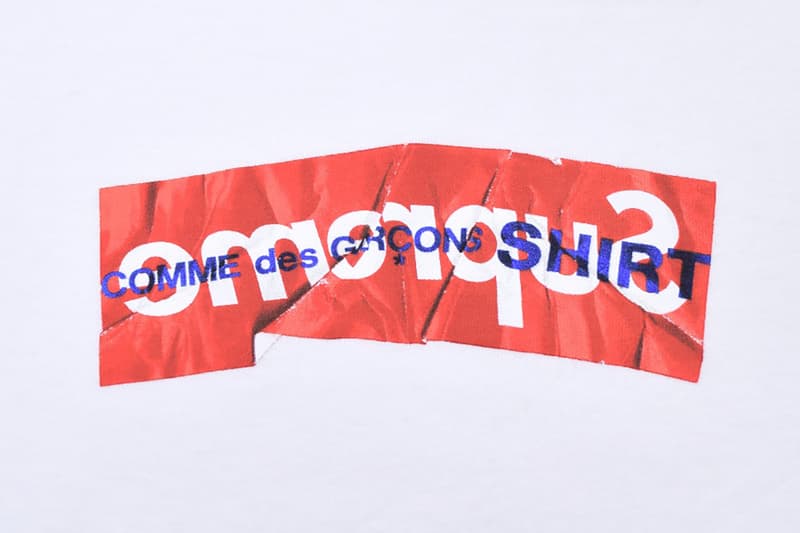
解析街头时尚品牌最爱用的 5 种字体
Supreme 与 COMME des GARÇONS 的 logo 能否诠释品牌风格?
字体,可视为时尚品牌的门面,是品牌与消费者沟通的桥梁。创意总监的更叠交替往往会带来字体重塑,旨在传达特定的情绪、力量、氛围,这意味著字体作为一种充满著复杂性的视觉语言,已成为时装、艺术、设计表达自我的重要工具。到底我们身边的街头、时装品牌或歌手、艺术家都青睐哪些字体,而这些字体,又是怎样反哺使用者,成为塑造品牌形象的重要一环。
Planet Cosmos
Raf Simons, Adidas
早前上映的《Ready Player One》成功打进 80、90 后观众市场,似乎再次强调源自上世纪 80 年代的游戏、科幻以及夜店文化正式回潮。Planet Kosmos 诞生于1996 年,丹麦图象设计师 Mads Rydahl 在日本漫画风格的基础上,创造出这款有著超高速摩托风驰电掣般神韵的字体,不但拥有日本漫画的风格,线条也颇具流畅性与未来感。虽然最初只是为某夜店创作,在互联网上免费开放下载多年,却在前年因被 Calvin Klein 创意总监 Raf Simons 和 Kanye West 同时买下字体的商用版权而进入大众视野。
而 Kanye West 早在 2016 年底就开始实际应用这款字体了,那段时间,他频繁在社交网络上分享自己穿著一条印有 Calabasas 字样的 adidas 运动裤。Calabasas 是他与 adidas 的首个合作企划,用的就是 Planet Kosmos,充满速度与未来感的科幻风格,不但完全击中了 Kanye 的内心(他是日本经典动画片《阿基拉》的忠实粉丝),也表现出与 adidas 三线 logo 近乎完美的契合度。无独有偶,在前年底买下 Planet Kosmos 的商用版权后,Raf Simons 就在同名品牌中小试牛刀,推出以「Venomous Friday」为主题的黑色卫衣与 Tote Bag,上面印有科幻感十足的 Planet Kosmos 字体。
有趣的是,字体设计者 Mads Rydahl 在接受《Racked》 的采访时表示,他并不想研究时装设计师们为何钟情于他的字体,也没有收取现金作为报酬,但他倒是向两位设计师要了一些个人私藏,包括新设计的衬衫、雷鬼音乐专辑等等。
SEGA
Sega
游戏株式会社是诞生于 1950 年代的一家日本电子游戏公司,生产家用游戏机及游戏软件,曾与任天堂、索尼电脑娱乐及微软并称「四大家用游戏机」制造商。今年年初以手术室主题成社交平台热门话题的 Gucci 2018 秋冬时装秀,除了以手持人头、《Game of Thrones》里的小恐龍等元素玩尽怪异时尚以外,一款全新的字体 Sega 也吸引了无数时装爱好者的注意。
SEGA 字体常见于 1980 年代充满迷幻色彩的街机游戏厅。创意总监 Alessandro Michele 在 Dad Shoes 鞋舌的 Logo、包包上以趣讽手法创造的「GUCCY」 字样上采用 SEGA,致敬 80 年代电子游戏文化。
Gothic Script
Yeezy
在尚未发明活版印刷之前,每本书都需要经过抄写员历时数月抄写,德国古腾堡为了模仿这些手写体,发明了这种艺术性还是远远大于实用阅读性的衬线体。是至今日,源于 12 世纪的 Gothic Script 已通过街头品牌、时装的运用、流行音乐的推广,掀起了一波「字体狂潮」。从 A$AP Mob 专辑,纽约品牌 SSUR、Matthew Williams 主导的创意单位 BEENTRILL,银饰品牌 Chrome Hearts,到 MISBHV、424、Born x Raised 等独立设计品牌…… 街头潮牌确实将中世纪的古老文字带回了现代。
2016 年 2 月,Kanye West 携手洛杉矶艺术家 Cali Thornhill Dewitt 共同打造演唱会「The Life Of Pablo」的周边商品 — The Life of Pablo 同名服装系列,包括 T 恤、卫衣以及牛仔外套,设计以清一色罗马字体歌词印刷为主。Cali 曾在接受独立杂志《032c》采访中提到这种字体的复兴:
「这个设计基于 80、90 年代的帮派文化,帮派成员死后人们会为他做一件这样的纪念 T 恤。」— Cali Thornhill Dewitt
Gothic Script 经常出现在上世纪 80 年代帮派成员的刺青及衣物上,也会用于印刷圣经,因此被西方人认为拥有保卫家园的宗教力量,更有一丝自我保护的意味。随后,Kanye 趁热打铁,借助 Yeezy Season 3 的发布,成功将此字体打造成全球范围现象级的流行。不过,也有设计师对品牌过量使用这种字体表示出担忧,试问那些脚踩 Yeezy 身著 Pablo 的年轻人,有谁真的了解 Season 3 背后卢旺达大屠杀的故事?或是 Gothic Script 背后的宗教意义及帮派关联呢?
Gothic Script 特殊的笔触与涂鸦艺术家的涂写工具相当相似,不出意料地也能与街头文化碰撞出火花。除了服饰之外,Gothic Script 元素不断地出现在音乐人的专辑封面和海报上,比如说唱团体 A$AP Mob 早在 Kanye West 之前就将该字体印在专辑和周边商品上。Vetements 2016 SS/FW 则以 Gothic Script 字体呈现如「Drink from me and live forever」等标语,并将其运用在夹克、卫衣和裤装上,带有几分暗黑浪漫的色彩。纽约时报曾指出:「Gothic Script 字体包含了十分多元的文化,并且折射出一种信仰与反叛。」
曾作为推动朋克运动主力军的朋克教母 Vivienne Westwood,恰恰选择了名为「Starnberg」的 Gothic Script 样式字体作为个人品牌的 Logo,打破时装品牌总是留给人中规中矩的视觉形象。英国设计师 John Galliano 在 2000 年 秋冬系列上亦选择大规模启用该字体。他将自己的照片、作品和新闻以报纸形式印在成衣上,版头就是以醒目的 Gothic Script 写著「Christian Dior Daily」字样。
Vivienne Westwood
Helvetica
论历史,它比不上 Bodoni(Vogue 杂志封面字体);论优雅,它亦比不上拥有法国血统的 Didot,论实用,它比不上 Times New Roman (论文专用字体),但它对现代主义的影响力无疑是划时代的,也是首款被纽约 MoMA 首次列为馆藏的字体;COMME des GARÇONS、RAF BY RAF SIMONS、American Apparel、苹果 iOS 7 系统、松下电器、纽约地铁站都用它,B Magazine 有一期还专门介绍了这款字体。
「Helvetica is everywhere. It’s like air. You can’t help breathing it in.」— 平面设计师,Michael Beirut
20 世纪上半叶,包豪斯运动席卷了整个欧洲,实用主义影响了建筑、绘画、工业及字体设计,无衬线字体凭藉容易辨识和阅读的字形,进入了设计界的主流。被誉为「无衬线字体的终极形态」的 Helvetica,以「刚正不阿」的形象、柔和中性的气质以及现代主义气息,受到了无数设计师、企业品牌的青睐。
Comme Des GarÇons
不按常理出牌的川久保玲为什么会使用看起来柔和中性的 Helvetica 作为 Logo 字体,很多人或许会认为这是一件有点反差萌、有点讽刺的事情。实际上,干净简洁的 Helvetica 与川久保玲有著不可言喻的默契:柔和中性支持开放性释读,同时又能展现丰富的个性和不言于表的自信。作家 Judith Thurman 曾在《纽约客》的一篇文章中提到:「川久保玲和 Coco Chanel 都是以平等为前提,认为每个女人都应该从自己的衣著上得到舒适与自信。」
在奉行 Logo 主义的今天,斜纹代表 Off-White™,而红底白字即象征著 Supreme;其极具辨识度的标识,一看就能看出是什么的品牌认同感。HBA 当年扮演的角色异曲同工,视觉冲击力十足的黑底白字「HBA」正是以 Helvetica 演绎。HBA 创始人 Shayne Oliver 在 2017 年入主时装老牌 Helmut Lang,其 Logo 也戏剧性地使用 Helvetica。1986 年,奥地利设计师 Helmut Lang 在巴黎创立了个人品牌,以极简主义街头风格、先锋大胆的设计风靡一时,Helmut Lang 的名字在 1980、90 年代的纽约成为被热议的对象。
Helmut Lang
2012年,时任 Saint Laurent 创意总监的 Hedi Slimane 除了大刀阔斧地将品牌更名为 Saint Laurent Paris,更一举将原 logo 的衬线字体改为 Helvetica,引起了轩然大波。Saint Laurent 长久以来都以优雅传统时装品牌自居,Hedi Slimane 在字体上的革新似乎抹去了创始人的痕迹,也可说与圣罗兰先生当年以「吸烟装」打破性别、颠覆想像的举动似乎一脉相承。
「尽管在品牌更名和 Logo 更新时引起了许多争议……这个变化也并非无中生有,而是追溯到品牌的历史和根源。」— Hedi Slimane
Saint Laurent
上世纪 60 年代,德国设计师 Karl Lagerfeld 在接手 FENDI 后,不但设计了双 F 标志,更使用了略微拉长的 Helvetica 字体作为企业标识和专用字体,带领著 FENDI 在 60 年代的绽放,Helvetica 无疑是它成为国际知名奢侈品牌的道路上举足轻重的一步。
从 1987 年起,A.P.C. 成为巴黎 Cool Kids 寻找法式中性风格的基地,看起来简单得循规蹈矩,实际上每一件单品都经得起岁月的磨砺推敲,充满著反消费主义和推动实用主义的哲学巧思。克制、折衷的 Helvetica 则能完美演绎一直以冷静态度处世的 A.P.C.。
A.p.c.
Futura
FUTURA 字体诞生于上世纪 20 年代,当年倡导无衬线新字体的设计师 Paul Renner 基于简单的几何形状设计出 FUTURA,字体加粗后几何感强化,带有强烈的未来感。字如其名,FUTURA 的名字本身就带有「未来」的含义 ,比起同属无衬线字体的 Helvetica 更棱角分明,审美上更具个性。
Supreme 标志性的红底白字 Logo 便采用了 Futura 字体,字体本身前卫鲜明的形象的确完美诠释出 Supreme 骨子里那股打破常规、挑战传统的叛逆精神。其灵感源自于美国著名艺术家 Babara Kruger 于 1980 年代创作的反对消费主义、支持女性主义的作品,Supreme 还因此激怒了 Kruger 本人。
「好的字体设计除了要具备实用性,还得兼顾审美上的需求。」— Paul Renner
虽说在 Raf Simons 掌舵下的 Calvin Klein 品牌 Logo 已不是我们熟悉的版本,但提起 CK,我们脑海里出现的那行字实际上就是使用 Futura 字体。 Nike 在品牌 Logo、广告和许多产品上,都使用了 Futura 字体,据了解,就连 Nike 内部员工使用的也是 Futura,可以说是 Nike 的御用字体。中村世纪一手开创的日本潮流品牌 visvim,以揉合了印第安民族风和日式的复古,追求传统、上乘的面料制造工艺,即使价格高昂依然受到众人追捧。藤原浩、Kanye West、Pharrell Williams、John Mayer 等人都是活体广告。其 Logo 虽采用了罕有的全小体字样,但仍不难辨认出 Futura 字体的特征,在传统与前卫之间取得平衡。
自《Ready Player One》上映以来,许多观众开始重看 1980 年经典恐怖片《闪灵》,其中预告片的片名就是使用了 Futura 的字体。导演 Stanley Kubrick 本人就是 Futura 的忠实用户,经典科幻片《2001 太空漫游》、以及其代表作《发条橙》还有《大开眼界》都在不同地方使用这个字体。
很多人都认为自己并不是设计师,也不懂排版,不会平白无故研究字体背后的意义,而字体作为文字的载体,并不只是印刷体上的油墨,不同形态的字体作为现代设计的重要一环,在现实环境的应用中,被赋予了不同时代、不同行业的人的自我表达。就时尚界而言,无论是街头潮流品牌,还是高级时装屋,无论是设计师,还是消费者,我们亦需通过字体,去窥视一个全新的世界。毕竟如果仅为跟风字体的视觉效果,而不了解文化的起源,那么品牌本身也将沦为行业审美疲劳的牺牲品。